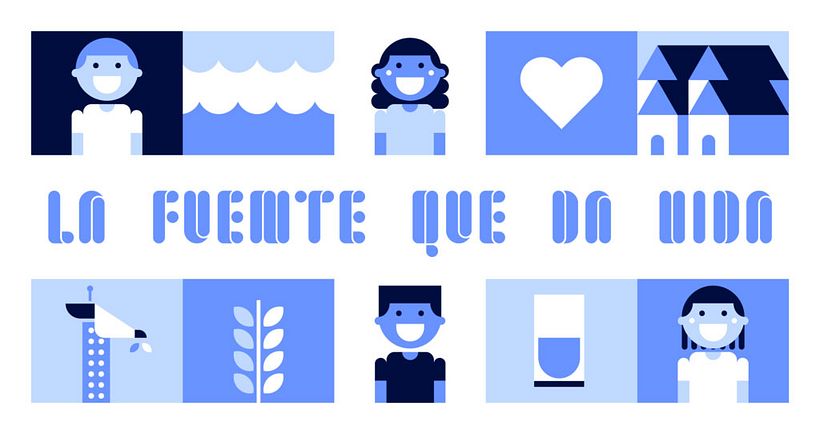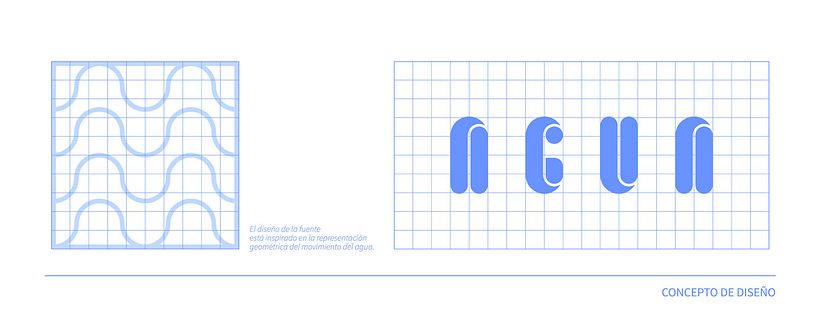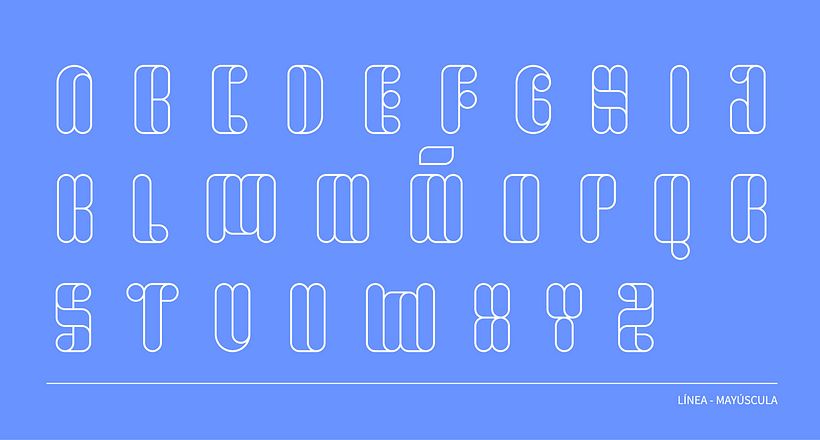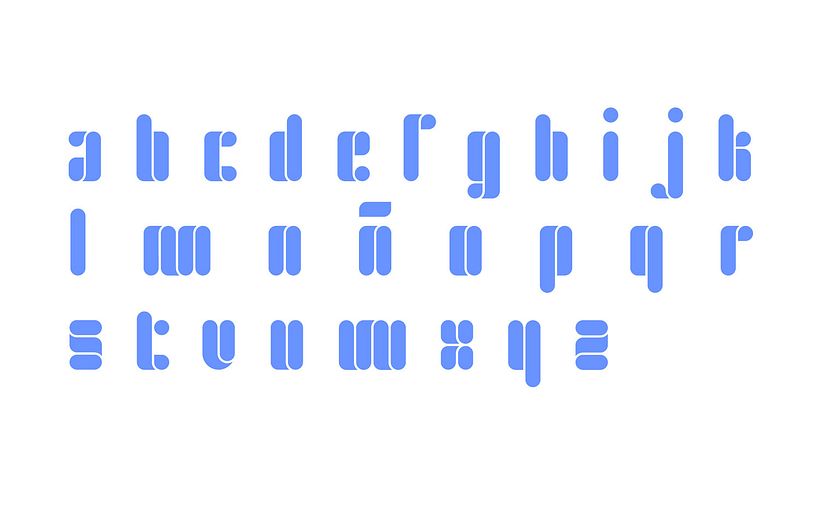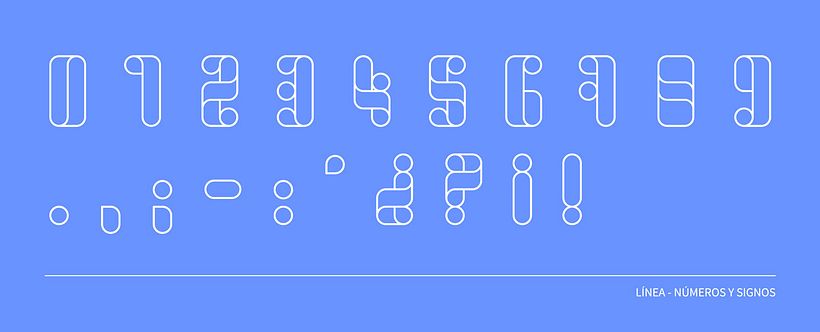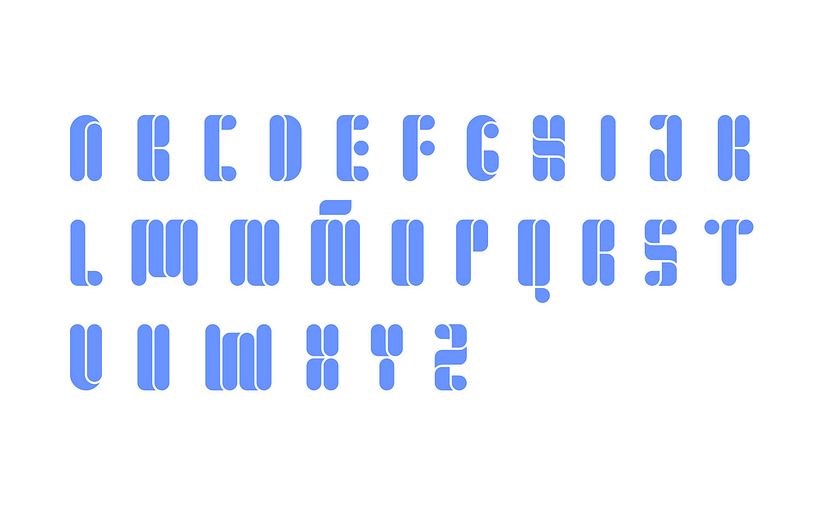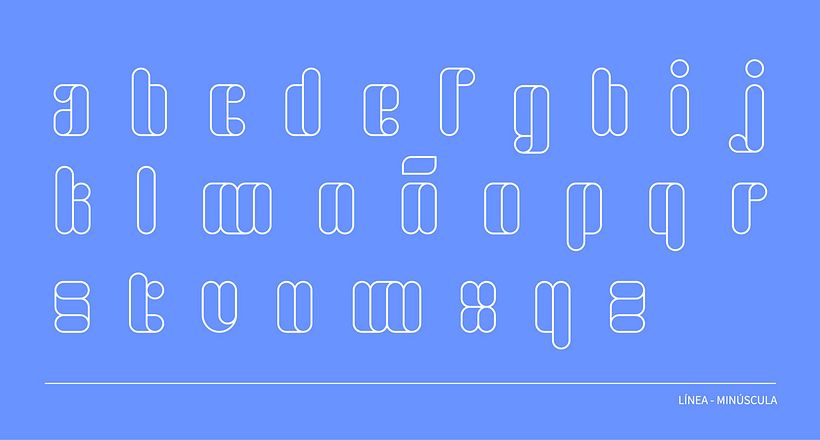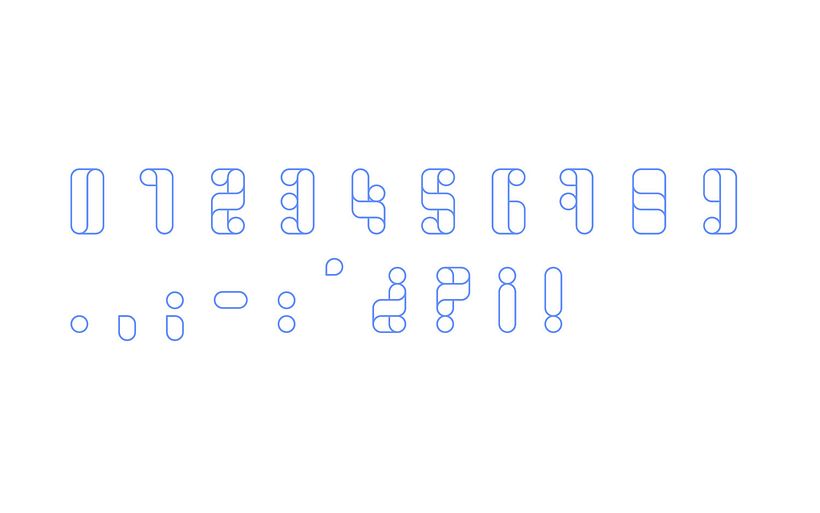
La fuente que da vida: una tipografía solidaria
Este estudio ha diseñado una tipografía que sirve como fuente de agua potable a quien más lo necesita.
Aunque que para muchos es un gesto tan cotidiano como abrir el grifo y disfrutar de agua limpia, actualmente existen más de 650 millones de personas que no tienen acceso a agua potable, esto se traduce en grandes deficiencias en la alimentación e higiene, que aumenta la mortalidad, llegando a causar más defunciones que cualquier tipo de violencia. Además, la falta de agua también incide en la baja escolarización infantil y en un reparto desigual de oportunidades. Con todo esto en mente, el estudio español azul recreo™ (@azulrecreo) ha diseñado 'La fuente que da vida' una tipografía para ayudar a acerca el agua a todas aquellas personas que la necesitan.
Por la fuente que da vida, sin embargo, no corre ni una gota de agua; se trata más bien de una tipografía que un estudio de diseño madrileño ha creado para recaudar donativos que se destinarán íntegramente a la causa que la Organización no gubernamental ONGAWA lleva más de 25 años defendiendo: la potabilización y saneamiento del agua en países como Nicaragua, Perú, Tanzania o Mozambique.
'La fuente que da vida' es una tipografía modular diseñada tomando como base la representación geométrica y el movimiento del agua. Está presentada en dos estilos, stencil y línea, que se adaptan a todo tipo de titulares y que servirá para reescribir el futuro de millones de personas que, gracias a las donaciones provenientes de sus descargas, podrán mejorar su acceso al agua potable.